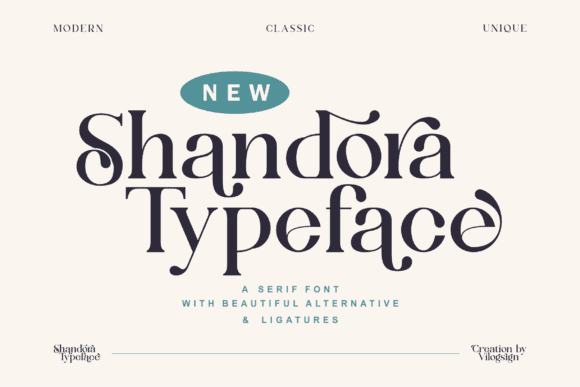
[Creativefabrica] Shandora Font (2021)
Название: Shandora Font (2021)
[Creativefabrica] Shandora Font (2021)
Shandora
- это смелый и выразительный шрифт с засечками.
Он имеет стильный, элегантный и современный вид, который можно использовать для логотипов, брендинга, приглашений, канцелярских принадлежностей, свадебных дизайнов, постов в социальных сетях и многого другого!